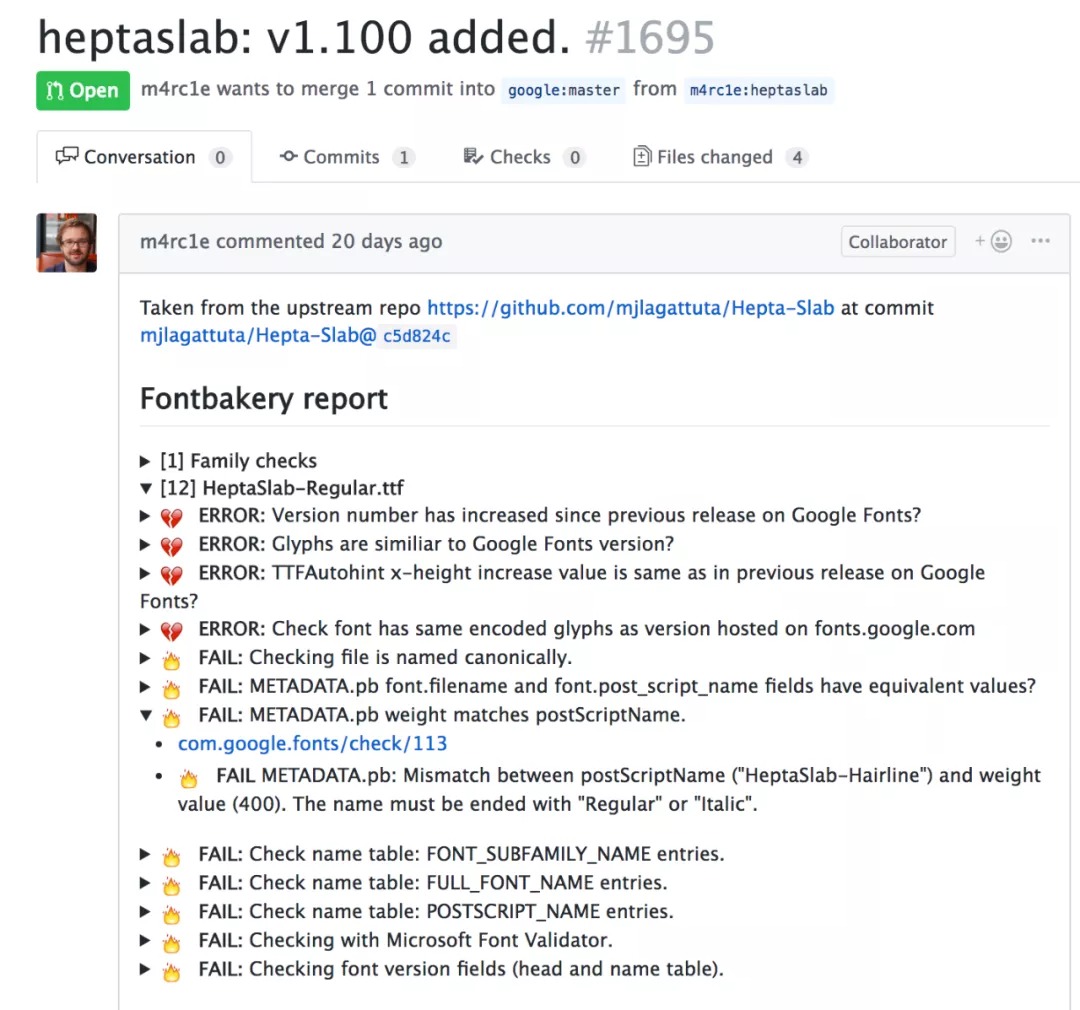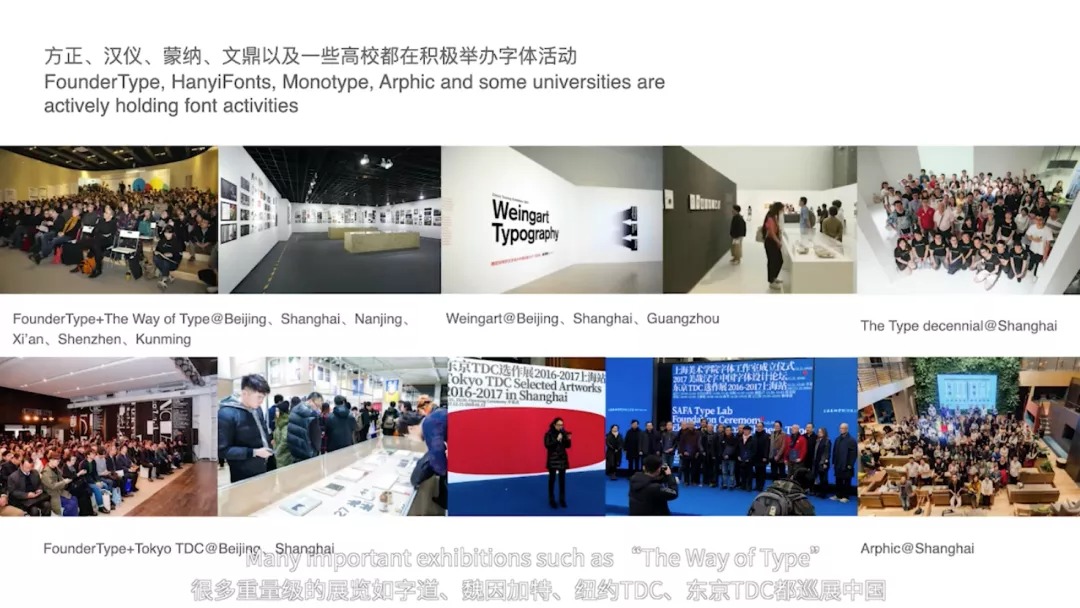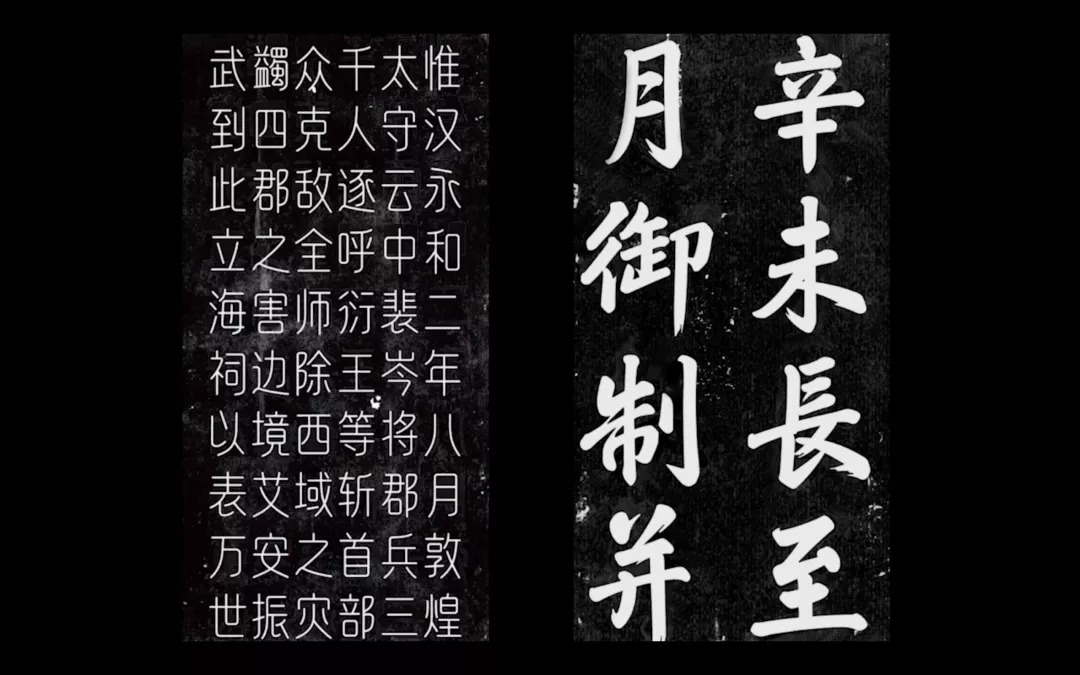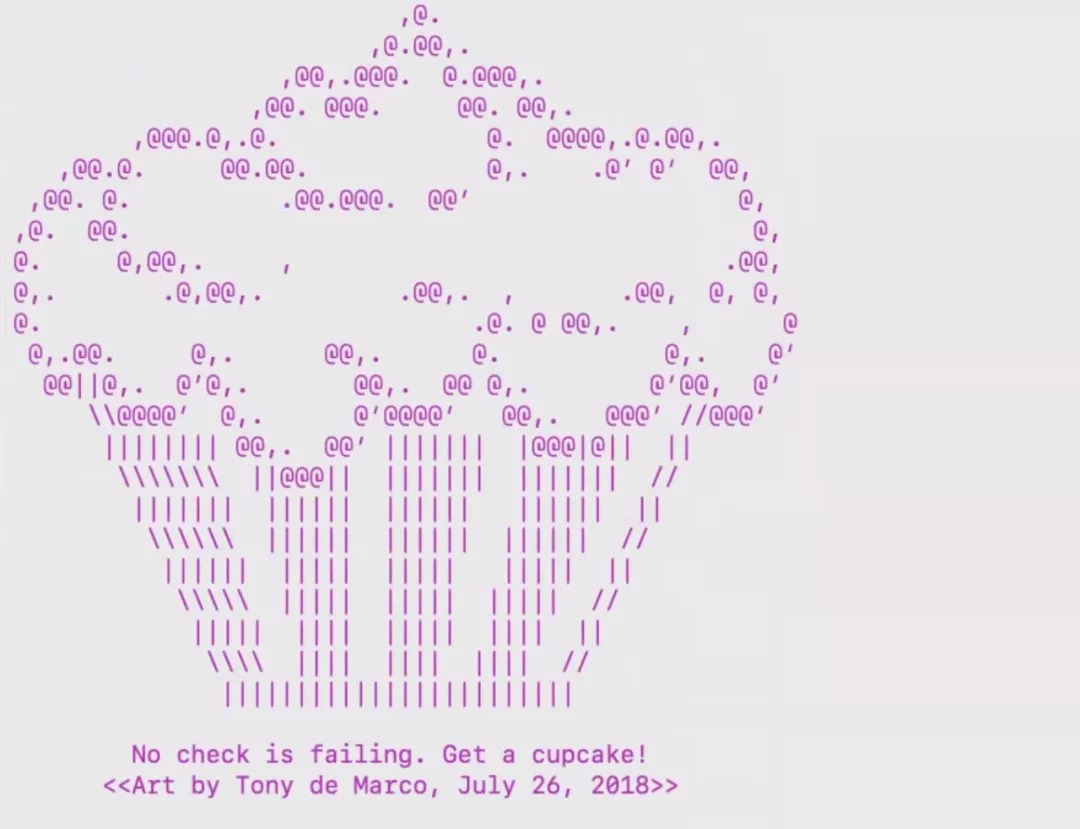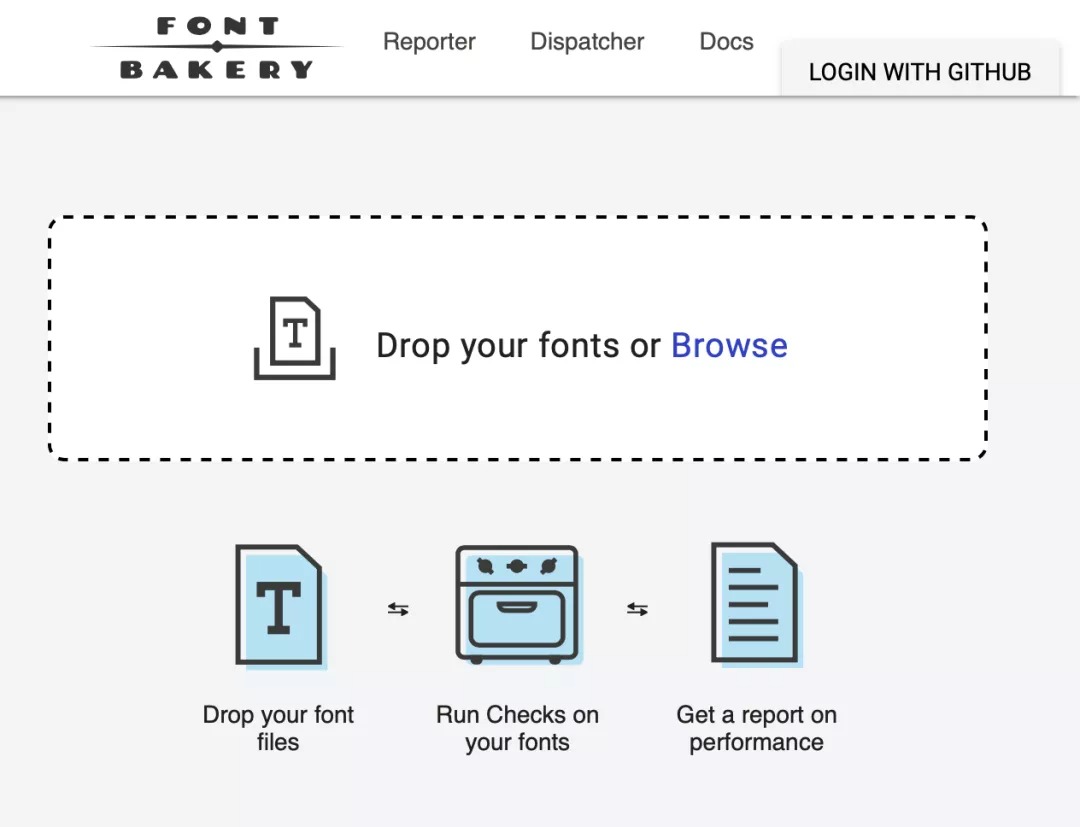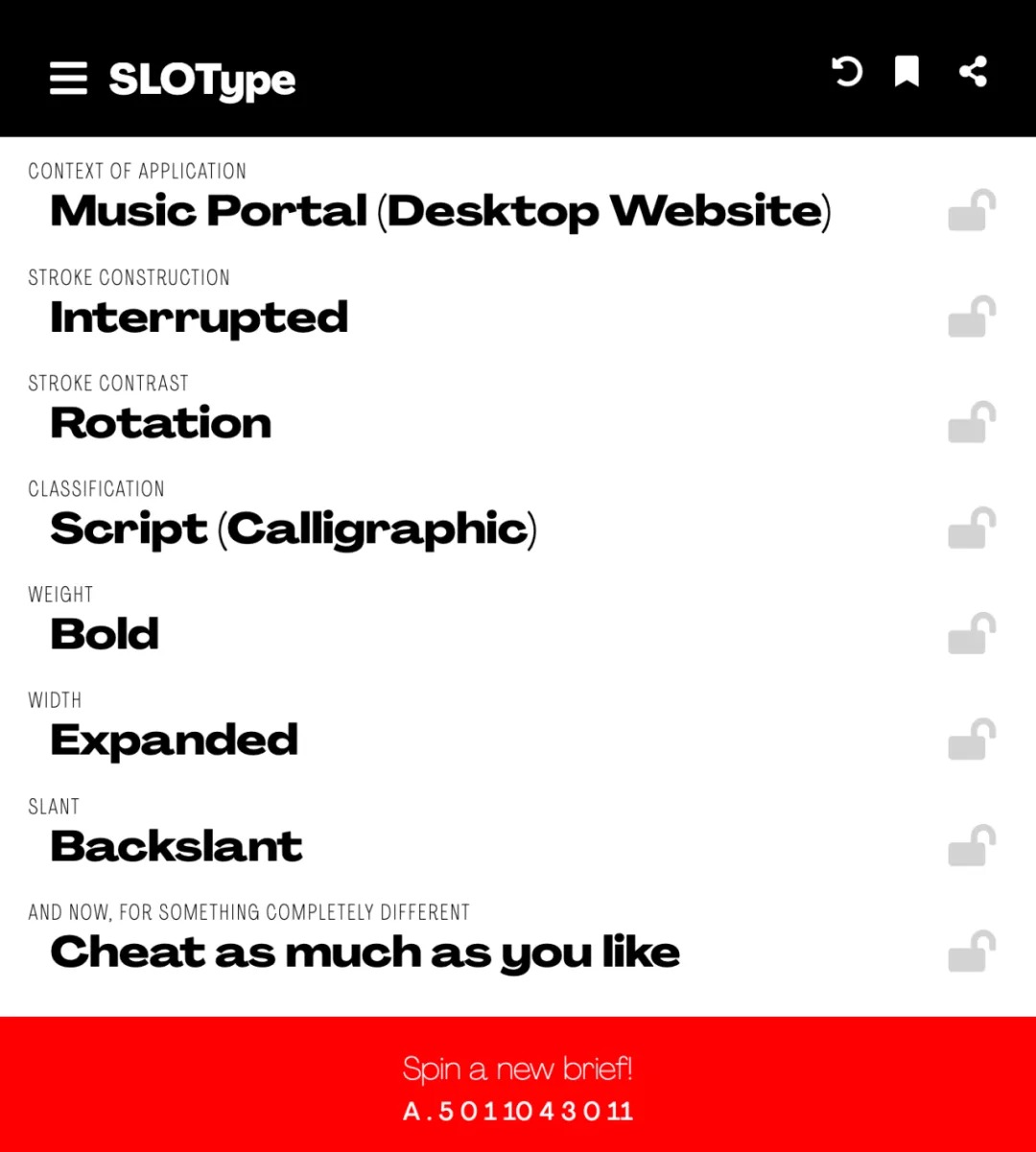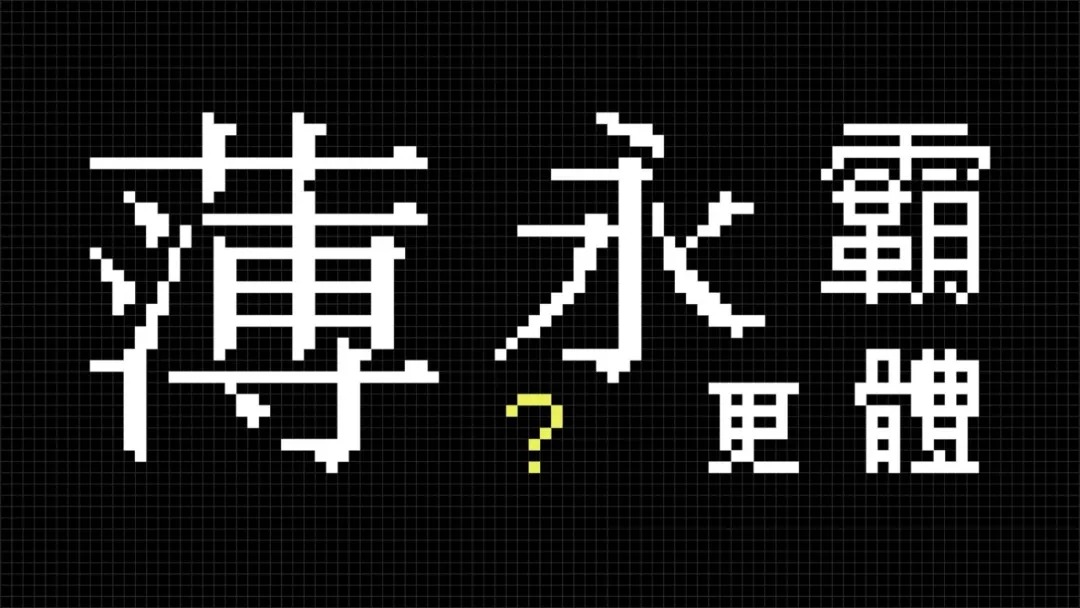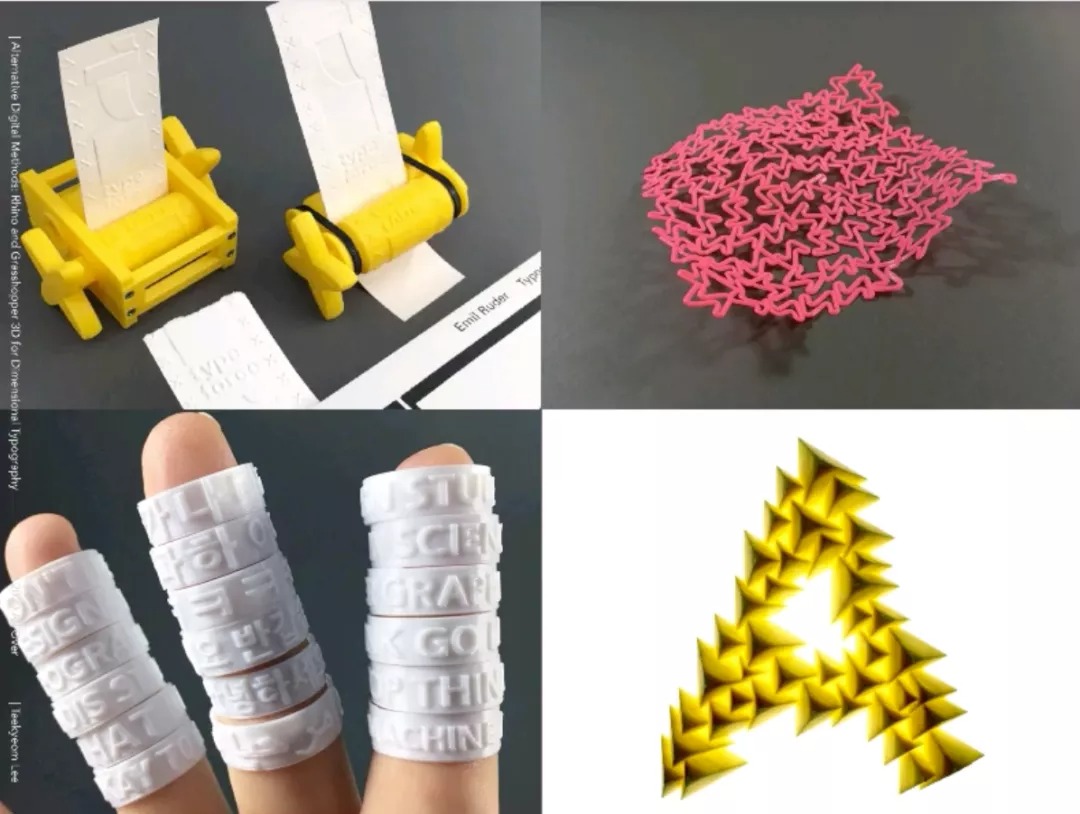
国际字体大会 ATypI · 2020 云端
2020 年 10 月,国际字体协会(ATypI, Associ­ation Typogra­phique Inter­nationale) 的年度大会如期举行;但与过往全然不同的是,原定于在巴黎举行的大会改成了线上举办——24 小时全球直播、多达 150 个会程,让五湖四海的文字设计爱好者前所未有地「共聚一堂」。
首次线上大会未免略显仓促和不足,但幸运的是,本站的编辑团队得以足不出户观看了整个 ATypI ,并在大会期间同步在微博和微信公众号平台上更新每日云端速报。ATypI 目前也在官方 Youtube 频道上陆续上传演讲视频,想要了解完整内容的读者可前往观看。作为视频导览和索引,我们也将之前的每日报道与相关内容在本页面悉数奉上。
此外,各位读者还可以从以下渠道获得更深入全面的报道,这些内容与 ATypI 官方公布的演讲视频内容并不完全重合:
工作坊集锦
工作坊包含非拉丁文字的书法练习、设计创意、以及软件和工具教学等内容。在此,我们为大家介绍其中的三款实用工具。
Font Bakery,检查字体文件规范的「烘培坊」
检查通过!奖励一个杯子蛋糕
检查后导出报告
Font Bakery Dashboard
谈论字体的设计时,我们必须注意到字体也是一款程序,一旦发布就必须保证规范和可用。Font Bakery 就是一款用于检查字体格式规范的工具,无论是在正式发布之前,还是日常的开发过程中,都可以使用 Font Bakery 查漏补缺,每一次检查的文档也都会保留下来,方便迭代与更新。
与其他类似的工具相比,Font Bakery 是一个开源维护的项目,它的标准库不断在扩大,满足变化的技术需求。如果是字体设计方面专家,但不会开发,则可以提交问题,指出需要检查的方面,由开发者来提供解决方案。现在,标准库除了可以检查 OpenType 等格式规范,也能检查是否符合 Adobe Fonts、Google Fonts 等平台的发布标准。
虽然 Font Bakery 需要使用 GitHub 运行,但官方提供了详细的安装和使用教程,还开发了 Font Bakery Dashboard 的可视化网页工具,直接通过拖拽就可以简易测试文件。而且软件完全免费,无论是设计师和开发者、个人设计师和字体厂商都可以使用。
SLOType:更讲究感性的字体灵感生成器
往期 SLOType 工作坊
在 SLOType 生成任务。
在直播中使用 Padlet 页面点评
熟悉字体灵感生成器的朋友们也许知道由 Erik van Blockland 设计的 TypeCooker 工具,它能够随机生成字体设计任务,让设计师基于诺尔泽(Gerrit Noordzij)的笔画理论,做字形创意练习。不过 TypeCooker 工具提供的主要是参数要求,例如粗细、字宽、衬线类型等。
而这堂工作坊介绍的 SLOType 工具则是设计师们在 TypeCooker 的基础上创造的,它结合了音乐家 Brian Eno 和 Peter Schmidt 创作于七十年代的经典锦囊卡片套装 Oblique Strategies 的内容,为设计任务加入了感性元素。在 SLOType 高阶版的任务中,你将得到「我的名字是弗兰肯斯坦」「尽可能地作弊」等脑洞提示,并试图将其与其他设计属性结合,让头脑风暴来得更猛烈一些。
另外,线上工作坊使用了 Padlet 这款网页应用,让参与者在网页上无需注册便能随时上传作品、展示点评,相比其他工作坊使用 WeTransfer 甚至网盘等工具来说,显然更直观而具有互动性。
犀牛加蚱蜢,3D 字体上手不难
Taekyeom Lee 的玩家秀
五秒迅速获得成就感
这款「字形丘陵」的曲线变化都可以按照参数生成和迅速调整(Taekyeom Lee 演示),左侧便是 Grasshopper 的「线路板」视觉化编程界面
如今文字设计进入实体空间、用于产品设计的需求与日俱增,字体和平面设计师有时需要一些成本低、学习曲线平缓的建模软件来进行跨媒介设计。毕竟说到底,更多的精力应该放在思考创作而不是学习软件上。相对经济和简便的 Rhino(犀牛)软件就成为了许多人的选择。来自爱荷华大学的平面设计助理教授 Taekyeom Lee 就展示了 Rhino 及插件 Grasshopper 的强大功能。
Rhino 中绘制模型的方式与一般 CAD 软件类似。而在文字设计方面,可以用 TextObject 工具快速选择计算机本地字体创造立体效果,或者直接导入 AI 文件。这个层面的操作十分便捷,几分钟就可以完成。
而 Grasshopper 是 Rhino 6 开始支持的视觉化编程插件,让曲线、平面和模型效果根据参数而灵活变化。选择不同的参数,你就能快速地将一条曲线分割成几十个节点,将二维字形平面连续旋转形成立面,或者在两条曲线中快速生成一个曲面……不同的函数之间还可以相互作为输出和输入项,让效果之间相互影响。
在导出阶段,则可以选择曲面的平滑程度,并生成不同格式的文件,满足 3D 打印或其他建模软件兼容的格式。但 Rhino 的渲染预览功能并不强大,这一点可以借助 V-Ray 等其他插件来辅助。Rhino 也有中文社区支持教程,软件可免费试用 90 天,感兴趣的设计师不妨小试。
ATypI 演讲亮点
从第二天开始,会议就进入了每天从早至晚十几场演讲连轴转的状态。当各位读者在官方 Youtube 频道回看所有演讲内容的同时,不妨配合我们的精选报道,了解重点和亮点。以下内容顺序较实际议程稍有调整,分别以日本文字设计、多语言多文字、字体技术、设计案例、设计研究与批评等主题来大致排序,方便大家浏览。
三十年代的手写体铅字,比数字时代更精巧
三十年代意大利铸字所 Nebiolo 出品的手写体铅字 Fluidum(左)和五十年代手绘广告(右)
三十至五十年代的欧洲是手写体铅字设计最繁盛的时期,Riccardo De Franceschi 的研究带领观众认识到了这一风潮背后的推动力量——现代广告业开始蓬勃,催生了对新颖醒目字体的需求,在宣传品中请艺术家绘制手写字能为广告加上点睛之笔。但请艺术家又太贵,于是手写体铅字满足了小型印刷社的经营需求,而他们的业务让手写体铅字大范围地运用于商务领域,广为大众所接受。这种书法、绘写、铅字设计之间的融会贯通,集大成地体现在手写体铅字中。
随着照相排版技术的兴起,手写体铅字反而没落了。哪怕是在数字时代,一些优秀的手写体的复刻作品反而简化了原版细腻的设计细节。是否有必要、以及如何在数字作品中重现当时的精益求精,在技术上和文化上也不失为值得探讨的问题。
Art Deco 风潮中,建筑师大展美术字身手
Art Deco 装饰艺术风格的建筑在巴西出现,比欧洲要晚十来年。但因为无需建造复杂的立面、建筑形态相对更符合几何特征,使建造成本大大降低,一时间巴西涌现出许多 Art Deco 建筑。这也影响到了附着于建筑上的文字,甚至建筑图纸中的文字设计。José Roberto D’Elboux 博士在五年多时间里收集研究了圣保罗在上世纪二十至五十年代的 170 多份建筑项目图纸,观察其中的署名标识、绘图风格、图纸手写标题、注释、以及建筑主体上的文字标牌等信息。它们呈现出多达四百余种手绘风格。
如何为乐谱制作一款字体
音乐和字体设计的发展时间轴,可以看到 150 年间字体从传统的衬线体发展到百花齐放的现代风格,但音符的造型几乎没有改变
来自加州的字体设计师 Dave Lawrence 研究了百年来的乐谱字体史,他首先展示了几种不同风格的乐谱字体适配:优雅的 Bodoni 风格,莫里斯的工艺美术风格,简约的无衬线风格……不仅是乐谱记号和歌词,也要在标题乃至花边上下功夫才能塑造一份风格统一的乐谱。与此同时,Dave 也注意到了设计乐谱字体的一些难点,而这些难点大多来自于作曲软件的限制。最后 Dave 提出疑问:如何在保留谱号笔画末端类似衬线的圆点的同时,塑造新的乐谱风格?喜爱音乐的设计师或许可以挑战一下乐谱字体的设计。
霓虹灯下的华沙
在丰富的工作坊和讲座之余,本次 ATypI 特设观影环节,首先播放的便是波兰导演 Eric Bednarski 执导的 Neon 纪录片,为大家讲述一段鲜为人知的华沙霓虹史。
在苏联模式下的波兰,尽管社会经济并不景气,但霓虹成为了人民美好生活的一种象征和宣传需求。无论是战前流光溢彩的街道夜景,还是战时社会党派利用霓虹宣传造势,抑或是战后伴随冷战和城市化的霓虹的衰落,还是保护传承意识的再度兴起,霓虹灯的命运变迁反映了华沙复杂而动荡的历史。
影片中,Bednarski 采访了位于华沙的霓虹博物馆的创始人之一 Ilona Karwinska,她收集了大量冷战时期的霓虹标志,以及一些当代设计师的霓虹设计,光线昏暗的馆内陈列着大量色彩斑斓的霓虹灯,让人回忆起昔日霓虹闪烁的都市夜景。
阿文数字利器 Sawād,真实还原苇管笔笔触
阿拉伯文对于许多人来说都很陌生,因为它和我们熟悉的拉丁文字几乎截然相反。书写阿文最主要的道具是苇管笔(Reed Pen),但现代人显然更习惯使用尖头笔,在数字环境下更是如此,这让阿文在屏幕上较难还原书写感。但另一方面,OpenType 中的合字(Ligature)特性解决了阿文复杂的字母组合情况,这极大地提高了阿文字体的制作效果。但真正提高字体出品质量,还需设计师深入了解阿文知识和字形变化的规则。
鉴于此,伊朗设计师 Sina Fakour 凭借自身设计与计算机的双重背景,开发了传播阿文知识的平台 Sawād。Sawād 展示了关于阿文基础知识的文章和视频,支持英语和阿语浏览,并提供页边注释、可变字体调节字号间距、夜间模式等良好的阅读体验。此外,Sawād 还有两款阿文小工具,用于教学的 Morakkab 和 书写工具 Kalamos。
平面设计中的种族歧视
Edwina Lee(文鼎科技):文鼎书苑宋——一款适用于多种场合的响应式中文宋体
谭泽源(汉仪字库):中国佛经字体设计
刘钊(中央美术学院)等:ATypI 国家代表报告
刘宇(汉仪字库):中国书法对数码时代文字设计的启发
幕后花絮:万圣节派对
ATypI 最后一日正逢万圣节,各国友人在家中玩起了远程派对,刻一个南瓜头,穿上 Cosplay 服,为 ATypI 画上了一个欢乐的句号。
ATypI 2021–2022:更多形式,更多活动
考虑到世界情势,ATypI 也对会期和议程做了许多调整。本应在法国巴黎召开的 2020 年 ATypI 大会将延期至 2022 年春天。在此之前,作为 2022 年大会的预热,ATypI 还将在 2021 年 5 月初重启线上的字体技术论坛,并在 2021 年下半年展开一系列线上活动,包括每月的主题演讲,2021 ATypI All Over 以及各类论坛,让大家在家也可以参与各种字体活动。本站也将持续报道 ATypI 系列活动,敬请期待。